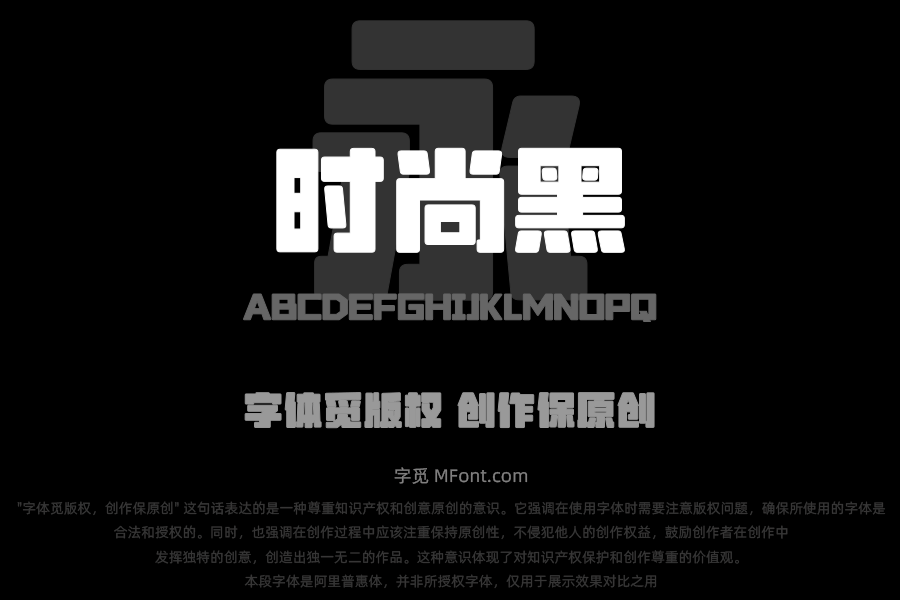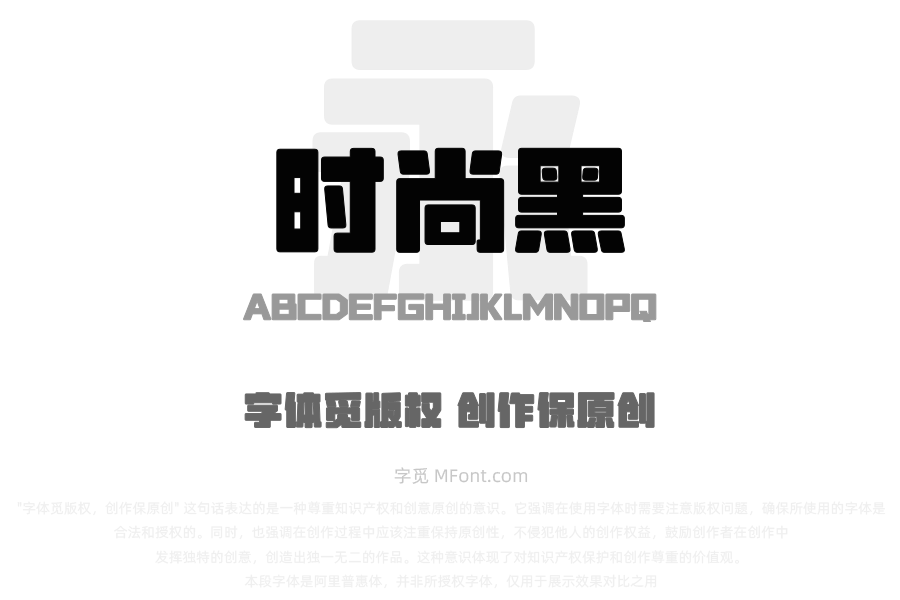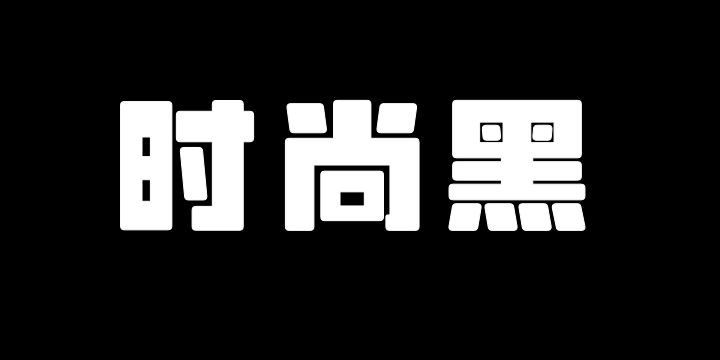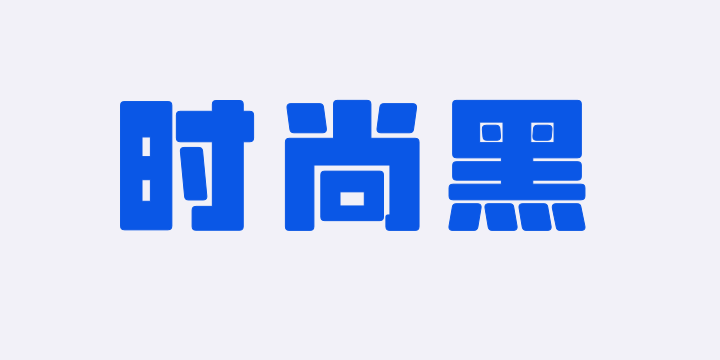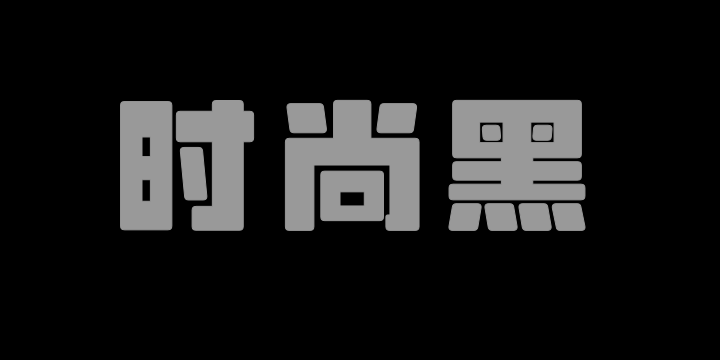
山海时尚黑
关于山海时尚黑字体字库信息
字体全名: 山海时尚黑
铸字厂: 山海字库
设计师: 山海字库
字体简介: 山海时尚黑,包含简体汉字6763个,是一款综艺标题黑体字体。该字体是一款具有强劲视觉冲击力的综艺风格标题字体。字形充实填满整个字框,造型硬朗,同时兼顾圆润性。直线与圆弧的笔画构成坚实有力。